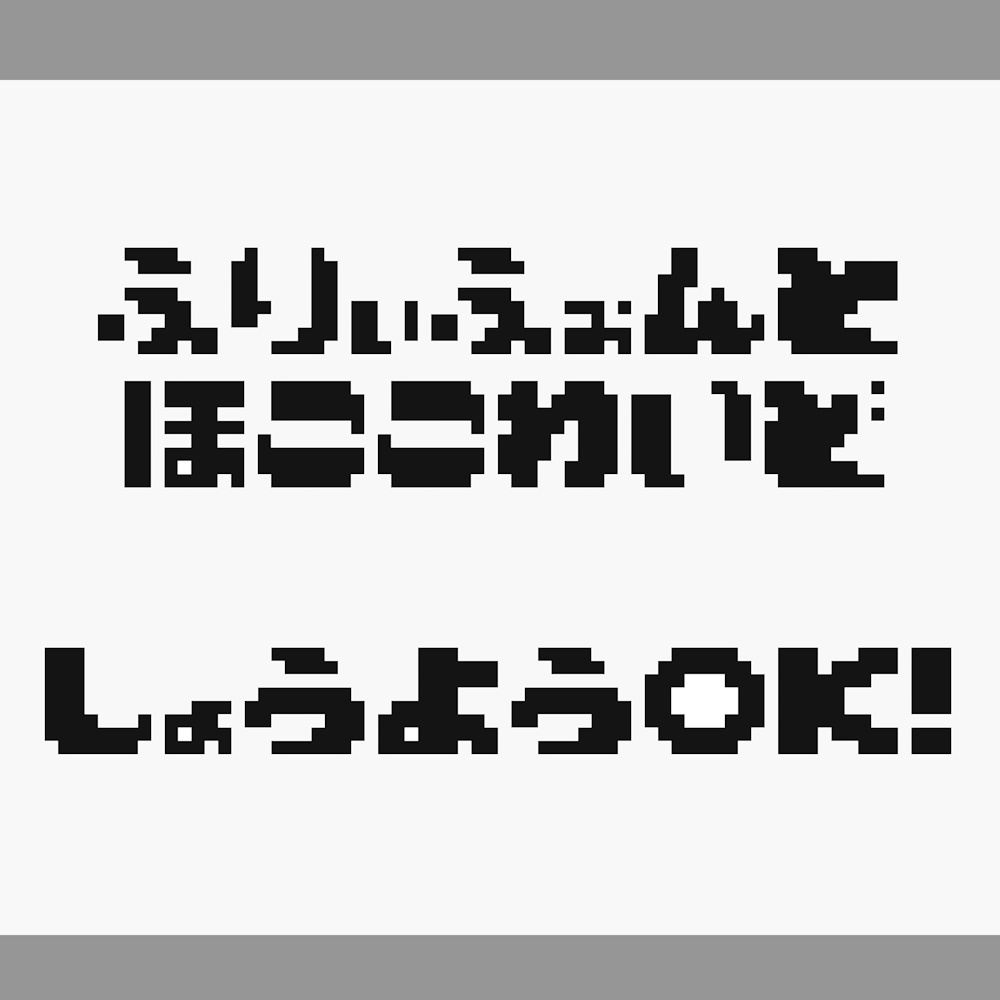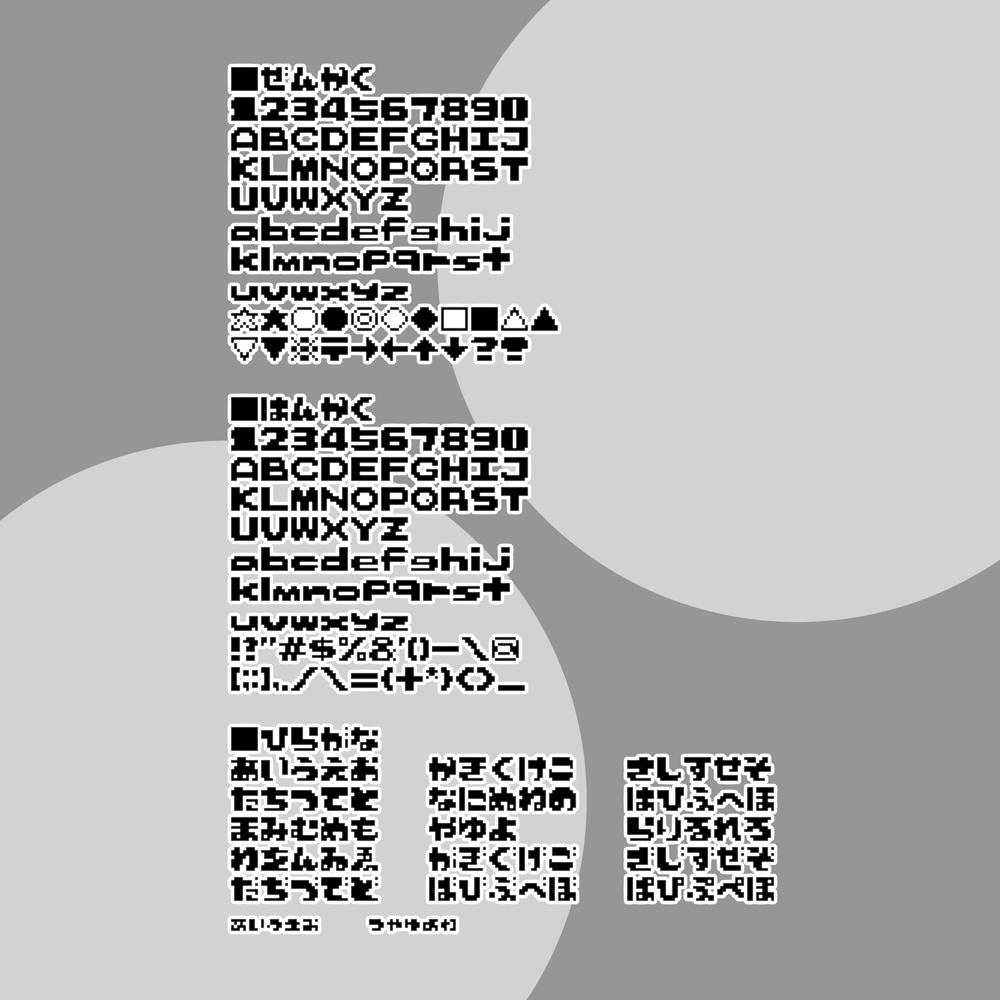
フリーフォント「ホココワイド」(無料・商用可)
「ホココワイド(Qma-hokokowide.ttf)」は フォント作成について何も知らない触手(加熱九真/shokushuQ)が https://www.pentacom.jp/pentacom/bitfontmaker2/ さんの力によって、手打ちしてつくったドットのフォントです。 何も知らないので横書きのことしか考えていません。 ■利用範囲 個人利用、商用利用、ウェブフォントやゲームなど独自性のあるコンテンツへの組み込みは自由です。 年齢制限が必要なコンテンツにもご使用頂けます。 ■禁止事項 犯罪行為や違法行為への使用、改変前のフォントファイルを単独で再配布することは禁止します。 商標登録など、第三者が本フォントを使用できなくなる行為は禁止します。 ■改変と再配布 収録文字の8割以上を改変し、本規約を改変前フォントの規約として明記・同梱することで再配布可能です。 ■免責 本フォントの使用により生じた損害について、制作者(加熱九真/shokushuQ)は一切の責任を負いません。 ■その他 必須ではありませんが、使用の際にクレジット記載があると嬉しいです。 ■収録文字について 全角・半角ともにほぼ同じデザインです。 全角と半角のピクセル数が2:1ではありません。 全角スペースはかなり中途半端な幅です(修正方法模索中) 半角スペースを1ピクセル分にしてあるので、それでうまく調整してください。 ■全角 1234567890 ABCDEFGHIJKLMNOPQRSTUVWXYZ abcdefghijklmnopqrstuvwxyz ☆★○●◎◇◆□■△▲▽▼※〒→←↑↓?! ■半角 1234567890 ABCDEFGHIJKLMNOPQRSTUVWXYZ abcdefghijklmnopqrstuvwxyz !?"#$%&'()-\@[;:],./\={+*}<>_ ■ひらがな あいうえお かきくけこ さしすせそ たちつてと なにぬねの はひふへほ まみむめも やゆよ らりるれろ わをんゐゑ がぎぐげご ざじずぜぞ だぢづでど ばびぶべぼ ぱぴぷぺぽ ぁぃぅぇぉ っゃゅょゎ